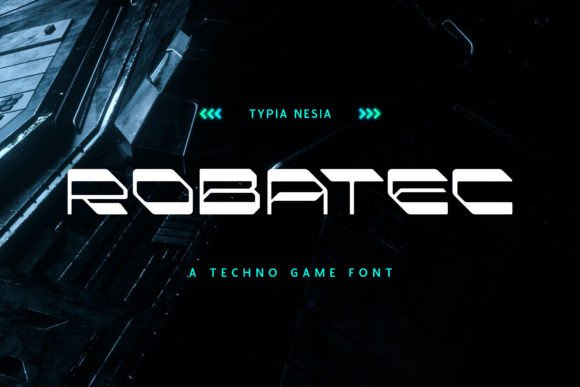
Robatec
Việc tìm kiếm các thành phần thiết kế phù hợp có thể là một thách thức, nhưng Robatec cung cấp một bộ sưu tập đặc biệt giúp nâng tầm công việc của bạn ngay lập tức.
Được chế tác với độ chính xác cao, Robatec cung cấp các vector sạch, kiểu chữ mượt mà và giấy phép thương mại để bạn yên tâm.
Cho dù bạn đang tạo sản phẩm POD (In theo yêu cầu), thiệp mời đám cưới hay đồ họa mạng xã hội, Robatec đều là một sự lựa chọn lý tưởng.